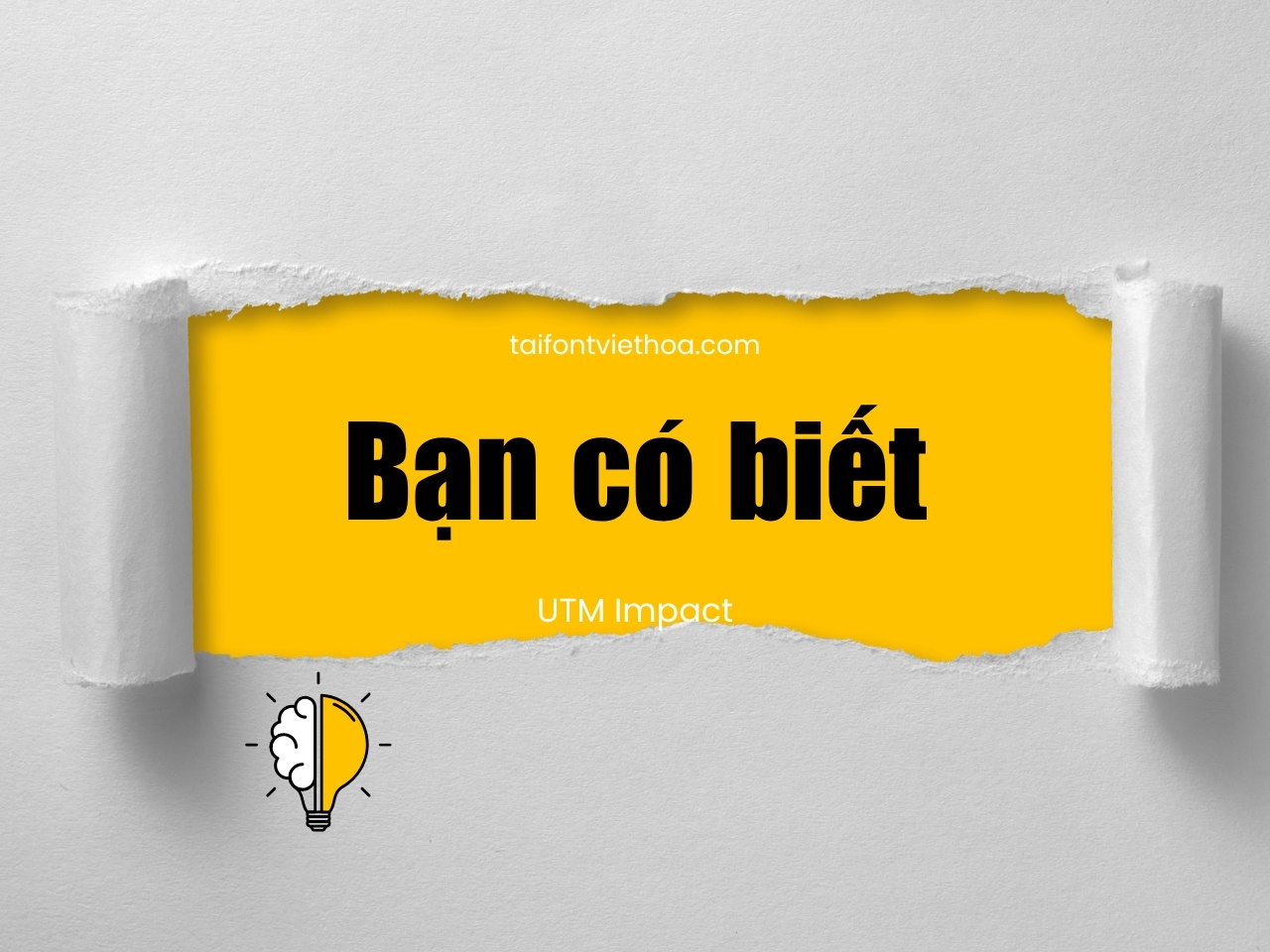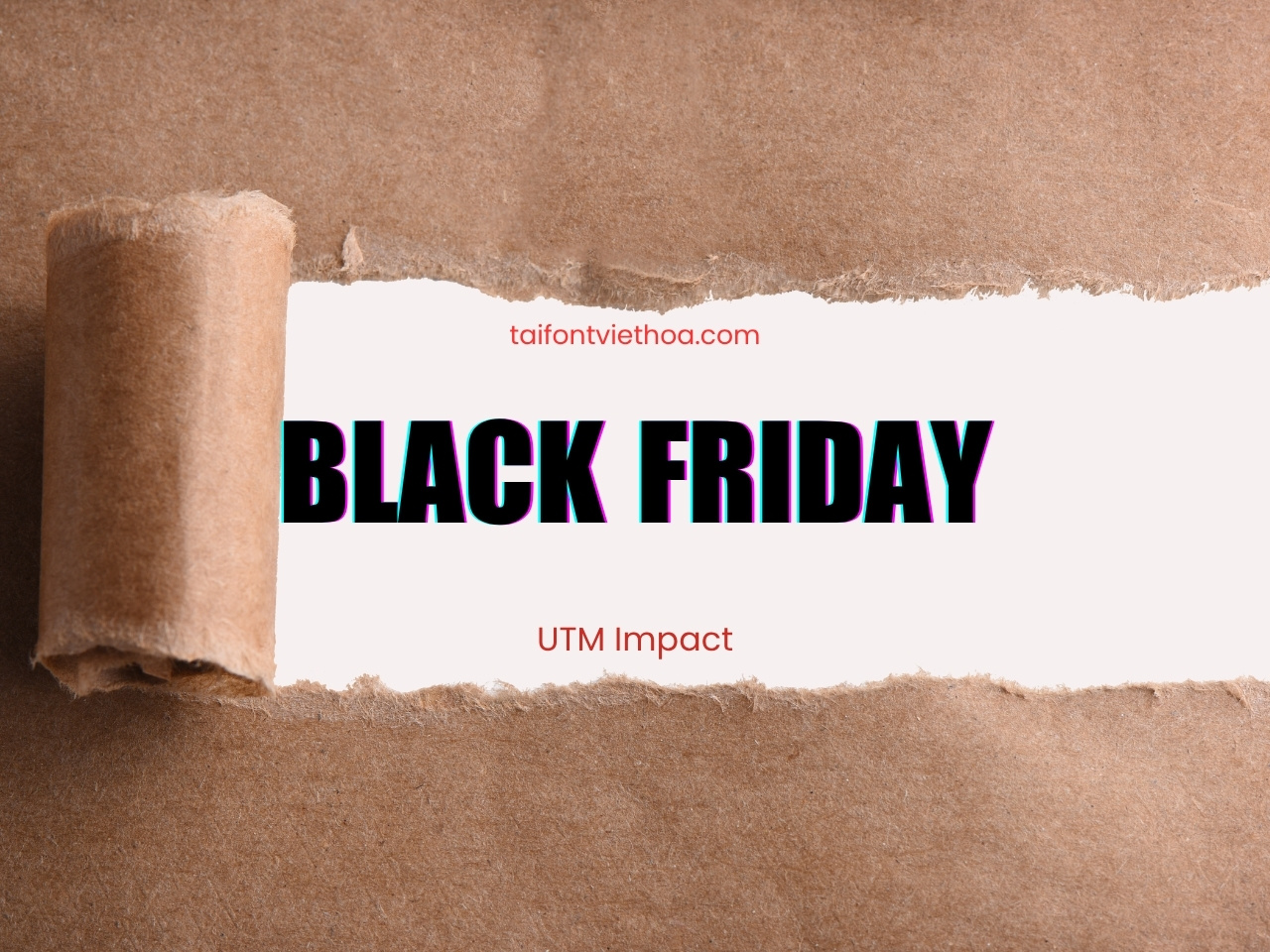
Giới thiệu về font UTM Impact
UTM Impact là phiên bản Việt hóa của font Impact – một kiểu chữ sans-serif đậm, nổi bật và rất được ưa chuộng trong thiết kế đồ họa để tạo điểm nhấn mạnh mẽ. Font gốc nổi bật với các nét chữ dày, chắc chắn và dễ đọc, đặc biệt phù hợp cho các tiêu đề, quảng cáo và poster cần thu hút sự chú ý ngay lập tức. Phiên bản Việt hóa đã được hoàn thiện để hỗ trợ đầy đủ tiếng Việt cùng hơn 100 ngôn ngữ khác, mở rộng khả năng sử dụng trong nhiều dự án thiết kế đa dạng.
Đặc điểm thiết kế và ứng dụng của UTM Impact
UTM Impact sở hữu cấu trúc sans-serif không chân, với các nét chữ dày, chắc chắn và sắc nét. Font có thiết kế đơn giản nhưng mạnh mẽ, giúp tạo hiệu ứng thị giác ấn tượng và dễ đọc trên nhiều kích thước khác nhau. Font rất phù hợp cho tiêu đề, logo, bảng hiệu và các thiết kế cần sự nổi bật.
Font thích hợp sử dụng trong thiết kế poster, bảng hiệu, nhận diện thương hiệu, quảng cáo, bao bì sản phẩm và các dự án truyền thông đa phương tiện. Các ngành nghề phù hợp gồm: giải trí, thể thao, quảng cáo, truyền thông và thiết kế sáng tạo.